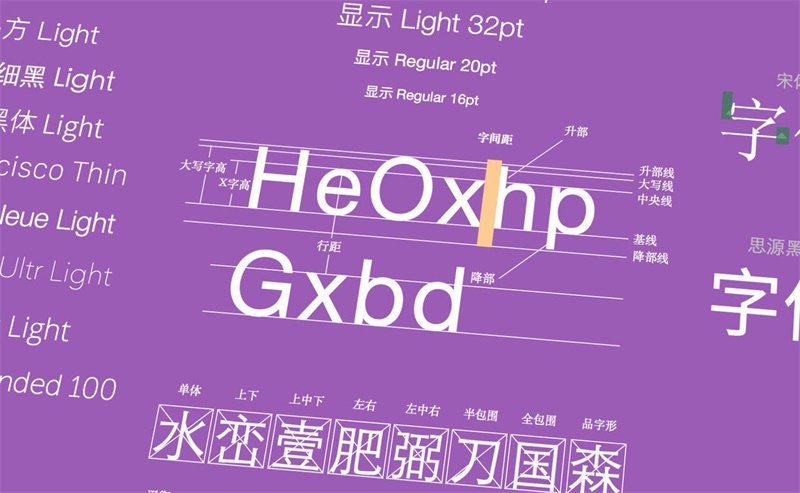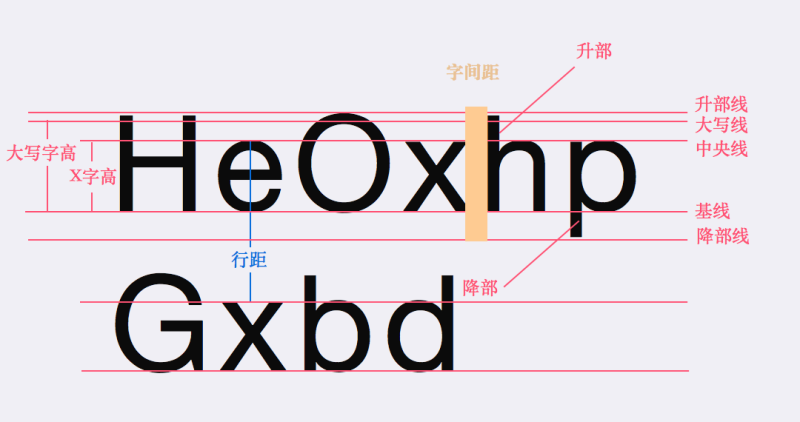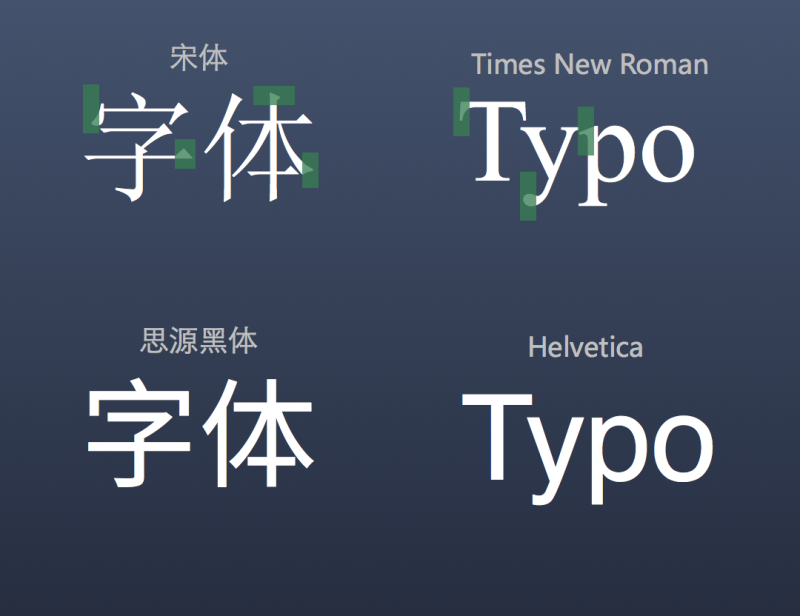
一份详尽全面的UI设计字体与排版指南
无论你是做网页还是App设计,文字内容总是能占到整个版面将近80%的区域。因此理解字体与排版对UI设计师来说非常关键。你需要始终把内容的可读性放在首位去考虑和权衡你对字体与排版的选择。
字体的基础术语
了解字体设计的基础术语非常重要,这些术语在介绍字体设计的相关文章中经常出现。比如 x-height(X字高)指的是从字母的基准线开始往上到最矮字母的顶端的距离,当X字高的比例相对大一些的话就能增加易读性。
汉字字形
在大多数情况下我们都选择使用系统自带的字体,比如微软雅黑、宋体、黑体等来定义标题和内容,但有时,我们在做Logo,banner设计时也需要通过对字体进行改造,来达到更加理想的效果。这时我们就需要掌握汉字的字形结构以及一些最基本的设计原则。
衬线字与非衬线字
在西方国家的字母体系,分成两大字族:serif(衬线字体)及sans serif(无衬线字体)。衬线字(下图中的宋体、Times New Roman)是指在字的笔画开始及结束的地方有额外的装饰,而且笔画的粗细会因直横的不同而有所不同。 相反的,无衬线字(下图中的思源黑体、Helvetica)就没有这些额外装饰,而且笔画粗细大致上是差不多。
衬线字的字体较易辨识,也因此具有较高的易读性。 反之无衬线字则较醒目。通常来说,需要强调、突出的小篇幅文字一般使用无衬线字,而在长篇正文中,为了阅读的便利,一般使用衬线字。在实际应用中,因为中文的宋体和西文的衬线体,中文的黑体和西文的无衬线体,在风格和应用场景上相似,所以通常搭配使用。
字体排版建议
在你对字体排版技巧了如指掌之前,首先需要保证你的内容能够简单且清晰地展现出来。优秀的文字与排版使我们更愿意去阅读,所以最好先关注你所设定的字体和排版是否便于阅读,然后再考虑为了美观改进行修饰。我们可以参考这篇英文指南:优秀字体排版的5条原则 并且将文中的这些原则应用到我们的App和Web设计中去。
iOS中的系统字体
随着iOS 9系统以及EI Capitan系统的发布,现在的系统字体变为了Apple自己设计的 [San Francisco]。iOS仍然在其他地方使用SF UI,而在Apple Watch中使用SF Compact。
San Francisco 有两类尺寸: 文本模式(SF UI Text)和展示模式(SF UI Display)。 文本模式适用于小于20 points的尺寸,展示模式则适用于大于20 points的尺寸。当你在你的app中使用San Francisco时,iOS会自动在适当的时机在文本模式和展示模式中切换。
注:如果你使用诸如Sketch或Photoshop的工具来进行设计,那么当你设置的字体大于等于20 points的时候,你需要切换到展示模式。iOS会根据字体大小为San Francisco自动调整字间距。
选择Body字体
为body text挑选合适的字体是最重要的。务必选择那些可读性强的,看上去干净易读的字体。我推荐的常用英文字体有:San Francisco, Helvetica Neue, Avenir Next, Open Sans, Museo Sans。中文字体则有,华文细黑,思源黑体。
字体的大小
在iPhone,iPad,iWatch 中设置的Body字体不应该小于11pt,这样才能被正常阅读。我们推荐的Body文本大小应该在15-18pt。
字体的字重
当我们设置更大的字体来获得更好的易读性的同时,我们也应相应地减小字体的字重(粗细),考虑Light,Thin或者Ultra Thin。过重的字体会太过醒目,从而影响其他内容的显示效果。
当字体大小为12-18pt时,使用Regular,18-24pt时,使用Light,24-32pt,使用Thin,当字体大小超过32pt时,建议使用Ultralight。以上都是建议值,你应该根据不同字体的显示效果进行设定使文字内容看上去清晰和精致,从而保持良好阅读体验。
现代字体都有多种字重设置:Regular,Light,Thin和Ultralight
合理设置行高,让文字也能够呼吸
行间距(leading)应该设置为字体大小的120%到145%之间。
在右边的例子中,行高设为了与字体高度相同的100%,而在左边的例子中,我将它设为145%。它们的显示效果有着非常明显差异。当字数进一步增加时,你更会发现阅读行距设置过小的大段文字会非常累。合理设置行高,也是一种留白的技巧,能够增强用户的阅读体验。
每行45-90个字
行长指单行文字的长度,如果一行中包含的字数太多,文本内容将会很难阅读。英文字符一般在45-90字比较适宜,而中文35-60字为宜。合理的行长使用户在行间跳转时非常感到轻快和愉悦,反之则会使阅读成为一种负担。
字体样式
字体样式对易读性和快速浏览非常重要,一般的原则是,被修饰的文本不应超过整个文本的10%,如果所有文本都都通过修饰被强调的话,那反而就不是强调了。当然,一次不应该同时使超过三种的强调样式。换句话说,不要在同一段文本中同时使用,颜色,字体改变,大小,下划线,斜体,粗体。
字体和排版是一门值得深入探索的艺术。每个字体的形成和发展过程都有着深远的历史可以追溯。当你设计的作品也能被称作艺术品时,那就是对你最大的肯定。